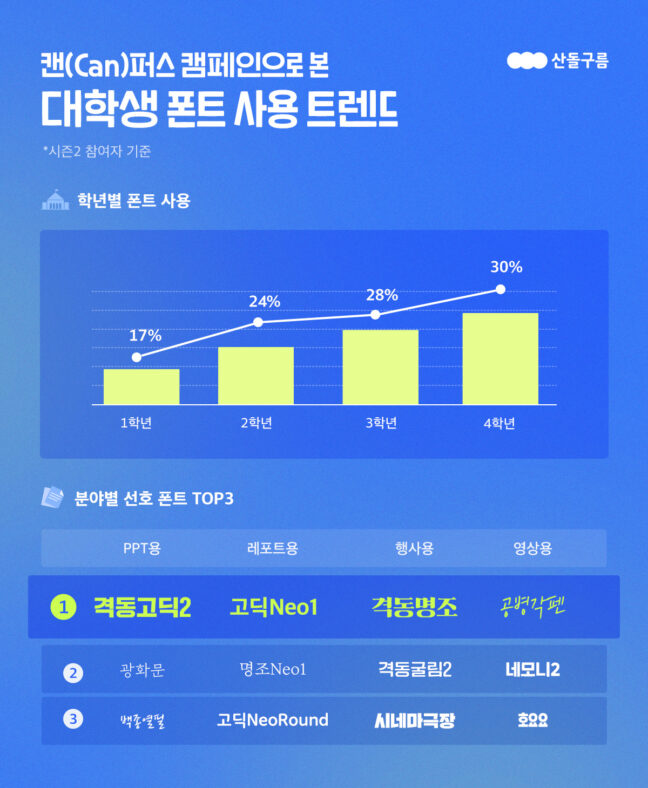
대학교 PPT 발표용으로 가장 인기 있는 폰트는?
산돌구름, 대학생 폰트 트렌드 발표
대학교 PPT용으로 가장 인기 있는 폰트는 개성 강한 제목용 폰트「Sandoll 격동고딕2」, 레포트용으로는 높은 가독성의 「Sandoll 고딕·명조Neo」 시리즈인 것으로 나타났다.
콘텐츠 크리에이터 플랫폼 기업 산돌은 자사 폰트 플랫폼 산돌구름에서 실시한 ‘산돌구름 캔(Can)퍼스 캠페인 시즌2’의 운영 결과, 이 같은 결과가 나타났다고 28일 밝혔다.
산돌구름 캔(Can)퍼스 캠페인 시즌2는 대학생을 대상으로 학업에 필요한 폰트와 템플릿 및 대학생활 꿀팁 등을 무료로 제공하는 캠페인으로 지난 2월부터 6월 말까지 실시됐다. 이번 시즌에는 전국 대학교 중 약 72%가 참여한 것으로 집계됐다.
이중 학년별 참여 비율을 살펴봤을 때 가장 높은 비율을 차지하는 것은 대학교 4학년(30%)으로 나타났다. 뒤를 이어 ▲3학년(28%) ▲2학년(24%) ▲1학년(17%) ▲4학년 초과학년(1%) 순이었다.
이 같은 결과는 대외활동, 취업 준비, 졸업준비회 등 학년이 올라올수록 폰트 사용이 더욱 필요해지기 때문으로 분석된다.
또 학과별 신청 현황을 살펴보면 디자인 관련 학과의 경우 39%, 디자인 비관련학과에서 61%가 신청한 것으로 조사됐다. 폰트 사용 목적별 선택 비율(활성화율)을 살펴본 결과 평균 사용 비율이 ▲레포트용(30%) ▲PPT용(29%) ▲행사용(25%) ▲영상용(24%)으로 모두 고르게 나타났다. 이를 통해 대학생의 경우 전공과 무관하게 레포트, 공모전, 발표 등을 위해 폰트를 다양하게 사용한다는 것을 알 수 있었다.
가장 선호 되는 폰트는 용도별로 달랐다.  PPT용으로는 개성 강한 제목용 폰트「Sandoll 격동고딕2」이 인기가 있었고, 레포트용으로는 높은 가독성의 「Sandoll 고딕·명조Neo」 시리즈 등이 많이 이용됐다. 영상 제작시 주로 사용된 폰트는 손글씨 폰트로 친근한 느낌을 주는 「Sandoll 공병각펜」이, 행사용 폰트로는 레트로한 느낌을 주는 「Sandoll 격동명조」가 많이 사용됐다.
산돌구름 캔(Can)퍼스 캠페인 시즌2에는 시즌1과 비교해 참여 인원이 약 90% 증가했다. 이는 폰트를 사용하는 범위가 점차 확대되며 폰트에 대한 필요성이 높아졌기 때문으로 산돌은 풀이했다. 또 시즌1 대비 시즌2에서는 캠페인 참여자의 폰트 구매 전환율이 약 110% 증가했다.